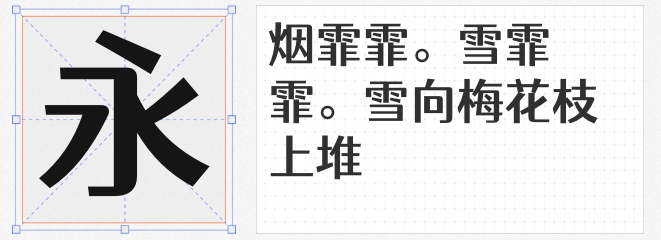
在设计领域,一款合适的标题字体往往能瞬间抓住受众目光,提升作品的整体质感。今天就为大家推荐四款免费商用的标题字体,它们各具特色,定能为你的设计增色不少。
优设标题圆在优设标题黑的基础上进行了巧妙改良,将原本犀利的尖角转化为圆角。这一改变,让字体在保留力量感的同时,更增添了一份柔和与亲和力。它非常适合用于那些需要传递温暖、亲切氛围的设计标题,如母婴产品宣传、公益活动海报等,能以柔和的姿态拉近与受众的距离。
斗鱼追光体2.0由斗鱼武汉研发部UED指导、品牌组设计成员主导设计。作为斗鱼的品牌字体,它承载着企业的活力、上进与娱乐特质。其笔画设计富有动感,线条流畅且富有节奏感,能够很好地展现斗鱼作为知名直播平台的科技感与娱乐性。在设计游戏直播、娱乐活动等相关标题时,使用这款字体能让品牌风格一目了然。
仓耳渔阳体 W05是仓耳字库在特殊时期奉献的公益字库。它结合了宋、黑二体的结构特点,部分笔画转折处采用圆角处理,实现了方圆结合的独特美感。字体厚重而不失灵动,既有着传统字体的稳重,又不失现代设计的时尚感。无论是用于文化宣传海报,还是商业广告标题,都能展现出独特的艺术魅力。
平方张亚玲黑方体是一款充满艺术气息的广告设计字体。它在保留黑体特征的基础上,融入了卡通体的特性,大大增加了字体的活泼性与趣味性。使用这款字体作为标题,能让设计作品瞬间充满活力,吸引年轻受众的目光,特别适合用于儿童产品、创意活动等领域的标题设计。
这四款免费商用的标题字体,风格各异,能满足不同设计场景的需求。设计师们不妨将它们收入囊中,为作品增添别样风采。